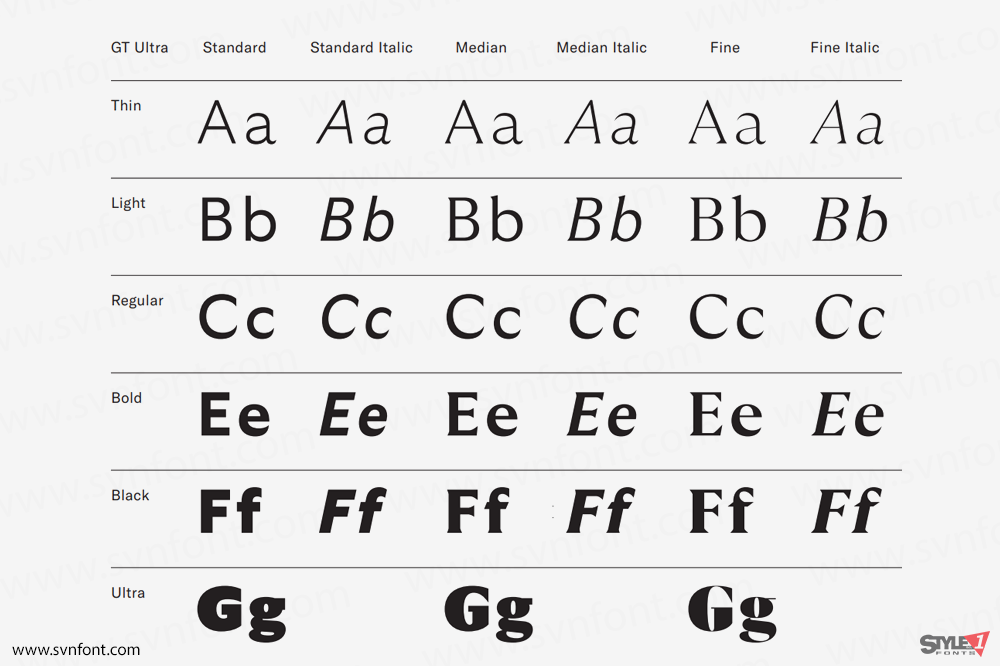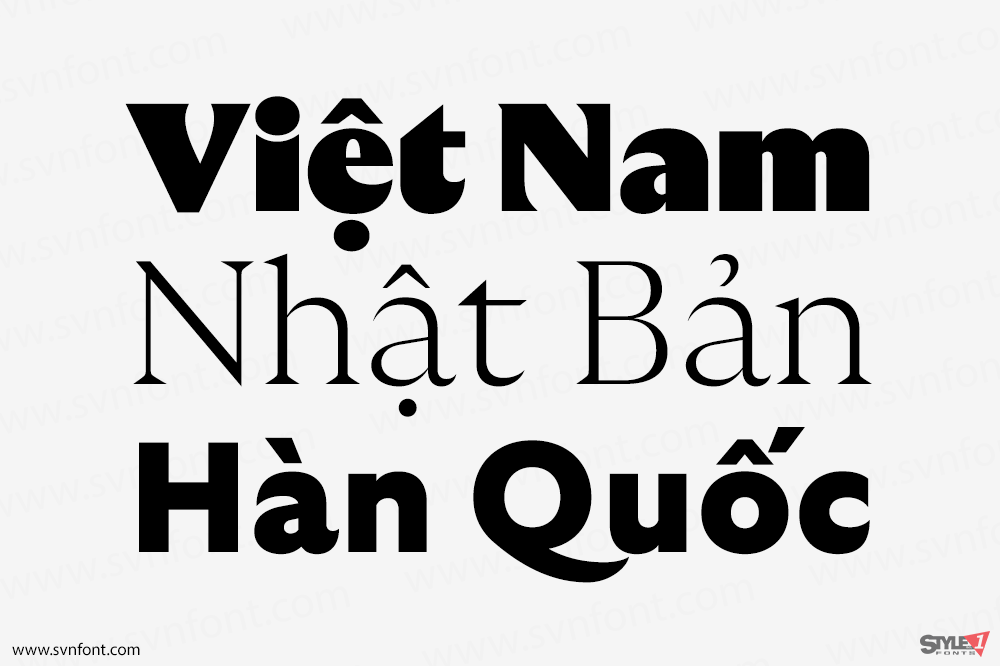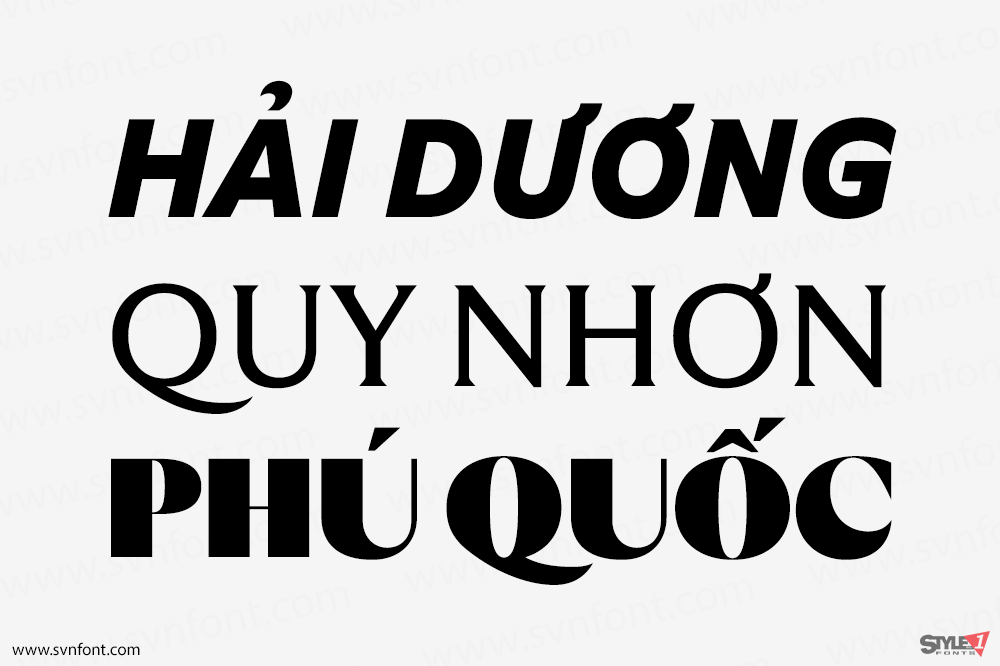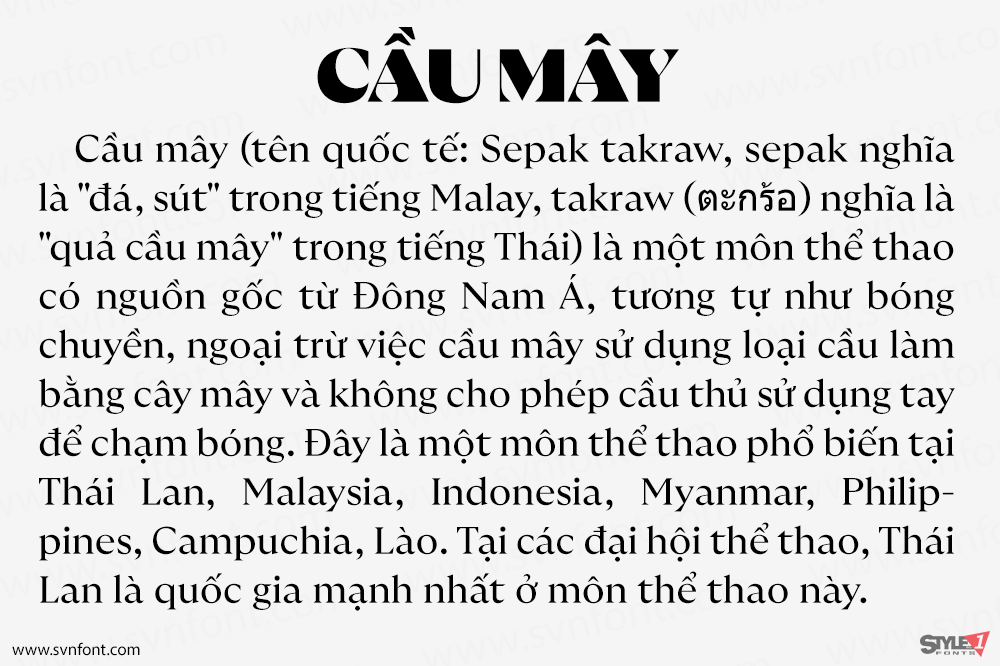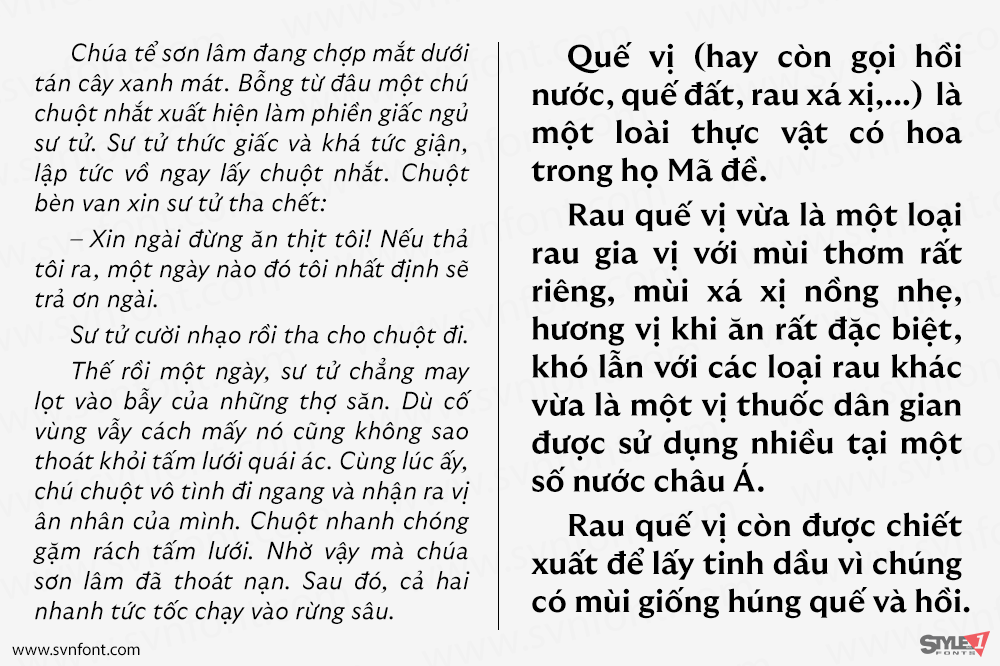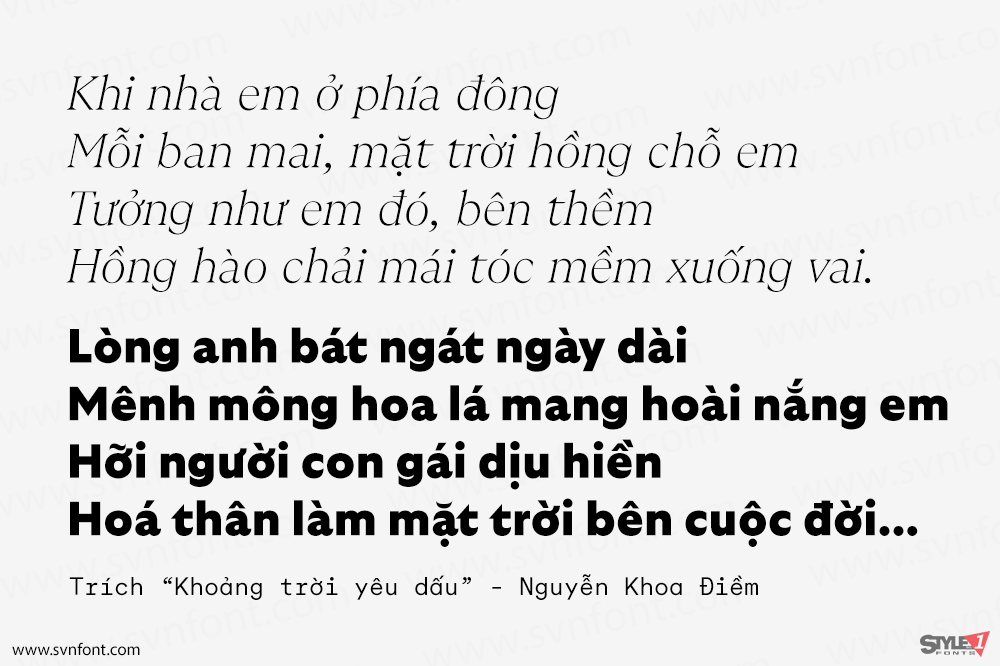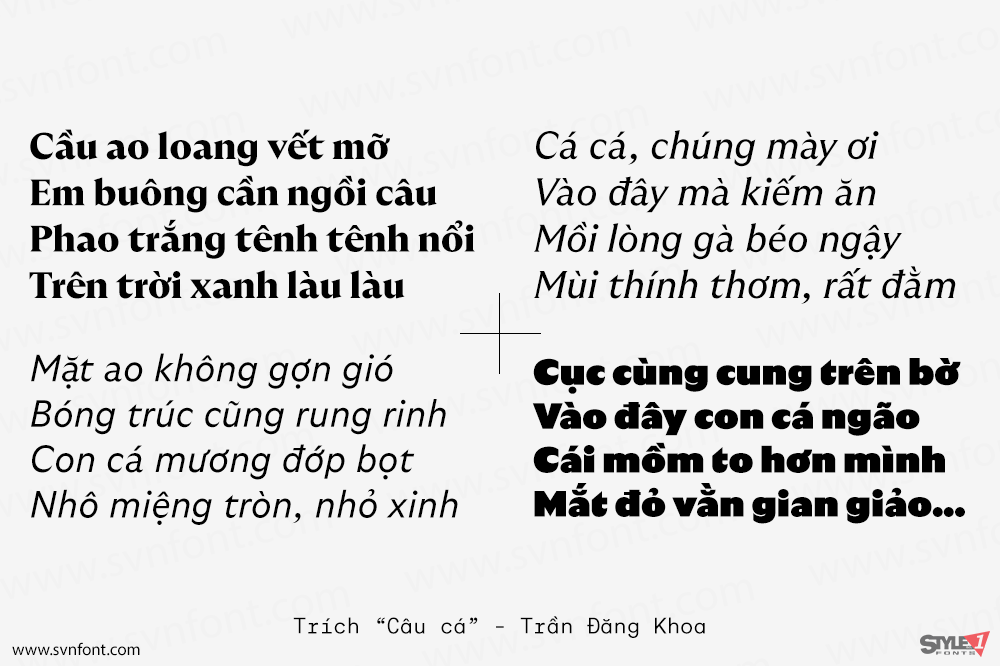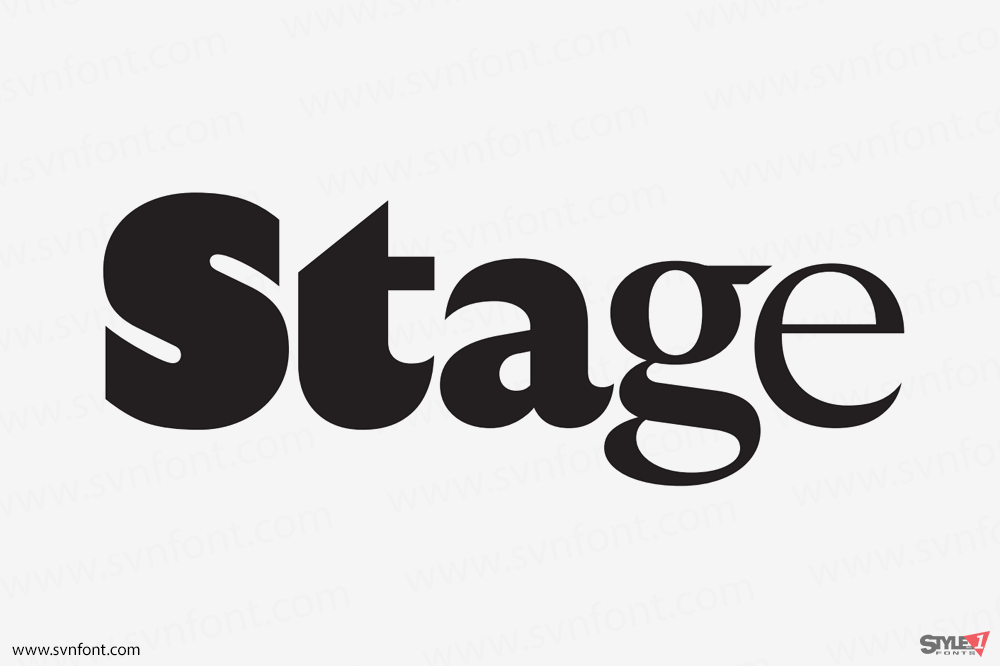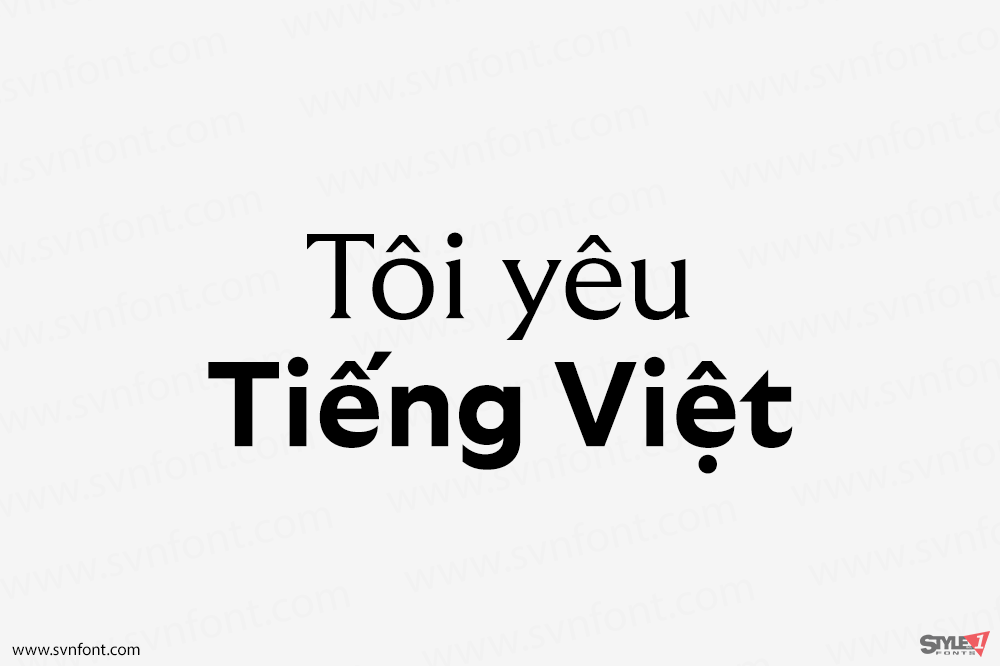
GT Ultra là một kiểu chữ “nhảy múa” giữa thế giới sans serif và serif, kết hợp thư pháp và cấu trúc. Hệ thống typographic đa năng này pha trộn bối cảnh hàng thế kỷ của kiểu chữ serif với sự năng động của sans hiện đại; thách thức định nghĩa của chính nó và đặt câu hỏi về kỳ vọng typographic đương đại.
Nhà thiết kế: Noël Leu, with additional help from Huw Williams and Grilli Type
Nhà phát hành: Grilli Type